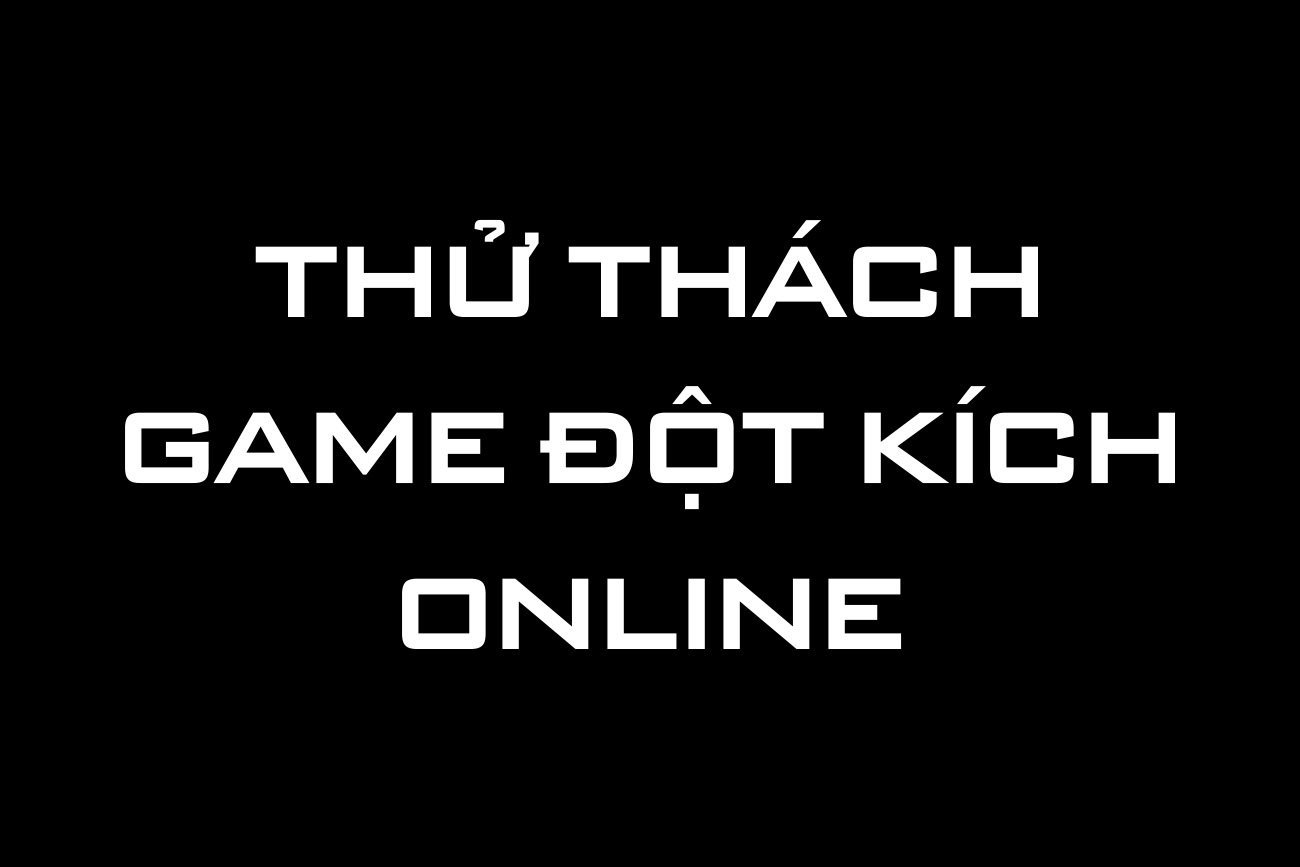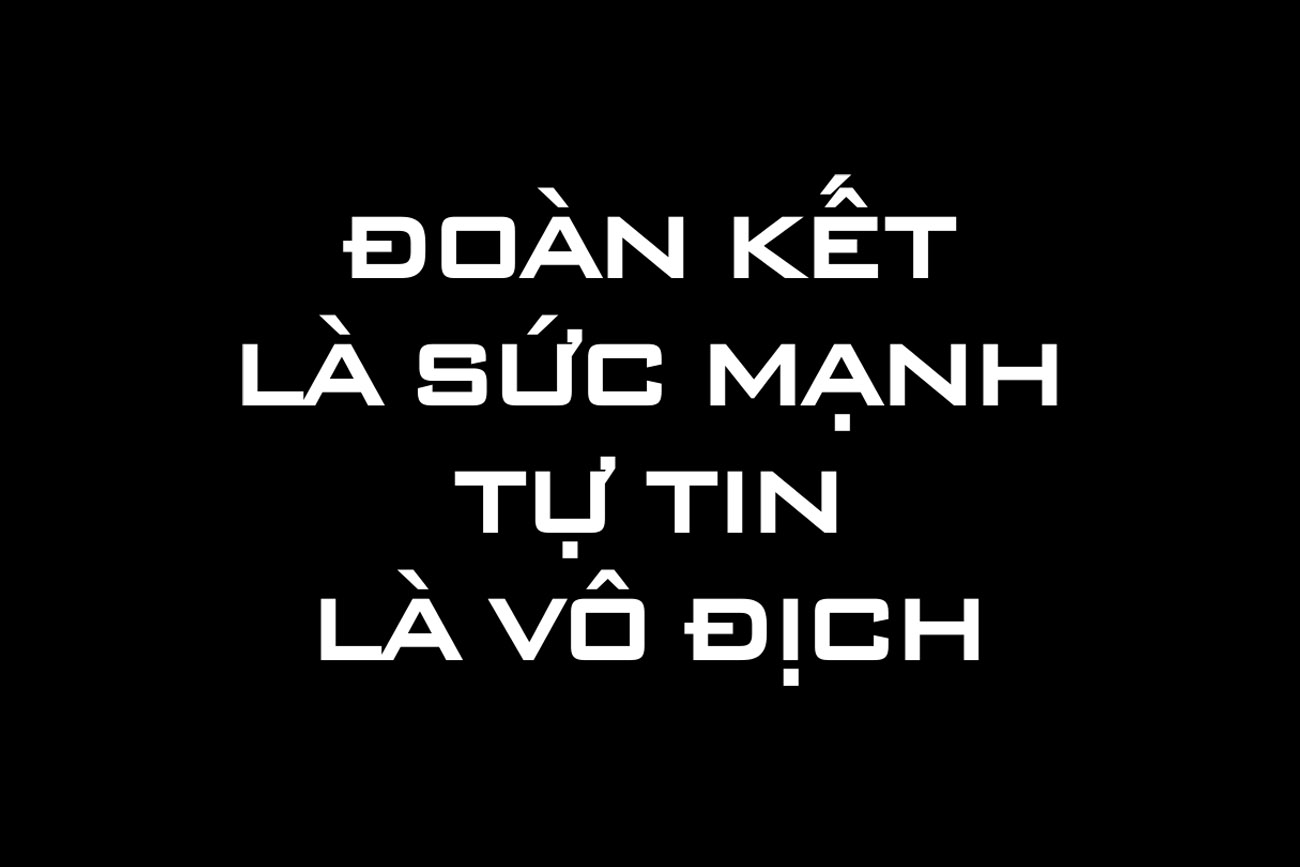
Tác giả Ray Larabie
Việt hóa Team UTM
Font UTM Banque là một trong những kiểu chữ Việt hóa được ưa chuộng nhất hiện nay nhờ phong cách hiện đại, mạnh mẽ và tính ứng dụng cao. Với thiết kế sans-serif vuông vắn, góc cạnh và đậm chất công nghệ, font này đặc biệt phù hợp cho các dự án cần sự dứt khoát, mạnh mẽ và gây ấn tượng ngay từ cái nhìn đầu tiên.
Nguồn gốc và Việt hóa
Font chữ gốc có tên Banque, được sáng tạo bởi Ray Larabie thuộc hãng Typodermic Fonts – nổi tiếng với những bộ font mang phong cách kỹ thuật số và công nghệ. Phiên bản UTM Banque Việt Hóa do nhóm UTM thực hiện, bổ sung đầy đủ dấu tiếng Việt theo chuẩn Unicode, giúp người dùng dễ dàng ứng dụng trong thiết kế mà không gặp lỗi hiển thị.
Đặc điểm nổi bật của Font UTM Banque
• Phong cách sans-serif hiện đại, đường nét gọn gàng, tối giản nhưng mạnh mẽ.
• Kiểu chữ vuông vắn, góc cạnh và cứng cáp, tạo cảm giác chắc chắn, dứt khoát.
• Cấu trúc chữ to rõ, dễ đọc, hiển thị tốt cả trong in ấn và thiết kế kỹ thuật số.
• Hỗ trợ tiếng Việt đầy đủ, mang lại sự tiện lợi cho designer trong nước.
Những đặc trưng này giúp Font chữ Banque Việt Hóa trở thành lựa chọn lý tưởng cho các thiết kế cần nhấn mạnh sự hiện đại, công nghệ và cá tính.
Ứng dụng trong thiết kế
UTM Banque Việt Hóa được đánh giá cao trong nhiều lĩnh vực sáng tạo, đặc biệt là:
• Thiết kế logo công nghệ, thương hiệu startup: thể hiện sự mạnh mẽ và chuyên nghiệp.
• Poster, banner sự kiện thể thao hoặc e-sport: tôn lên khí thế quyết liệt, năng động.
• Ấn phẩm truyền thông quảng cáo: tạo dấu ấn thị giác nổi bật.
• Slogan, tagline truyền cảm hứng: phù hợp với tinh thần font chữ thể thao và cứng cáp.
Vì sao nên chọn UTM Banque Việt Hóa?
Không chỉ đơn thuần là một font chữ Việt hóa, UTM Banque còn là công cụ mạnh mẽ cho các nhà thiết kế muốn truyền tải sự quyết đoán, hiện đại và đột phá trong dự án. Phong cách sans-serif khỏe khoắn cùng khả năng hiển thị sắc nét khiến font chữ này phù hợp với cả thiết kế in ấn lẫn digital.